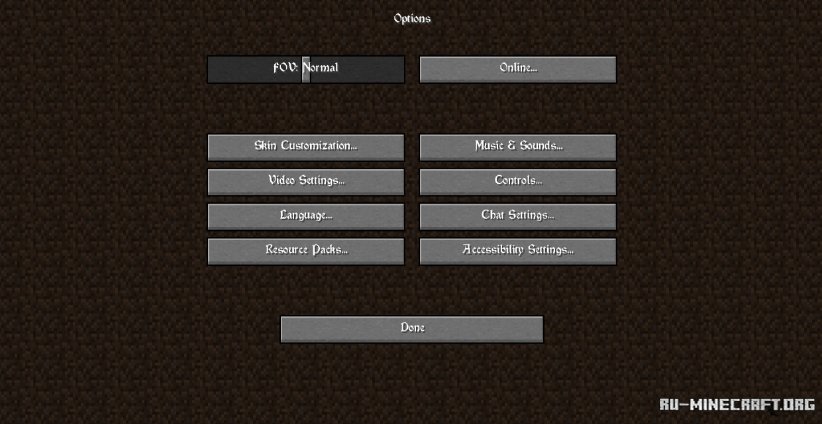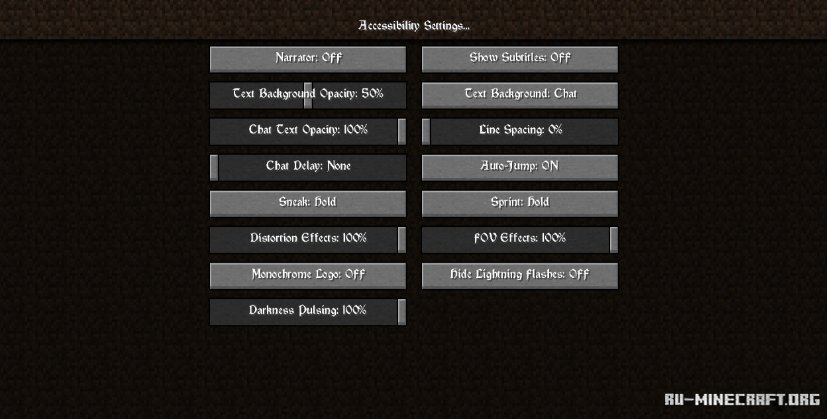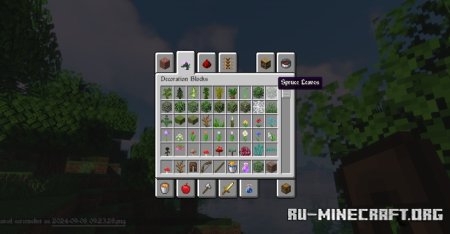
Скачать Gothic Medieval RPG Font для Minecraft 1.21.8
Неплохой пакет текстур под названием Gothic Medieval RPG Font, вы сможете открыть для себя интересный вариант некого готического шрифта в средневековом стиле. Это прекрасный шрифт, который в свою очередь позволит вам сделать шрифт более привлекательным. Скачивайте, и наслаждайтесь игровым процессом - оцените.